最近スマートフォンでソーシャルゲームを嗜んでいる。そこで気になるのは「三点リーダー」 … の形だ。
Android 4.1 のフォント変更
/system/etc/fallback_fonts-ja.xml のMTLmr3m.ttfの箇所をmigu-1c-regular/bold.ttfに書き換えれば欧文はRobotoのままで和文だけMigu 1Cに変わる。
/system/etc/system_fonts.xml のRoboto regularの箇所をMigu 1Cと書き換えれば欧文・和文ともにMigu 1Cに変わる。
「三点リーダー」 … の比較
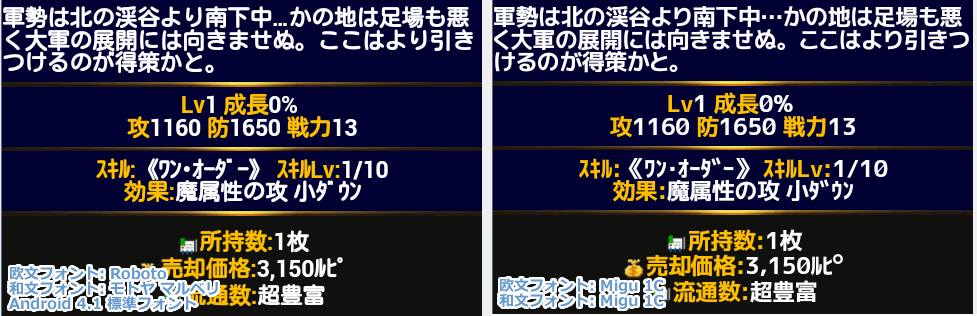
このゲームはなぜかbold体(太字)を使っているが、regularでも三点リーダーの見え方は同じだ。
Android 4.1 標準フォント環境では、三点リーダーは文字の下端に位置する。
欧文フォントもMigu 1Cにすると、三点リーダーは文字の中央の高さになる。
欧文フォント Roboto は「文字の下端に位置する三点リーダー」のglyphを持っていて、Migu 1Cは「文字の中央の高さに位置する三点リーダー」を持っているので、こういうことになる。
Android 4.1 標準フォントの「三点リーダーは文字の下端」は、なんとなく気になることもあるが、スマートフォンユーザーのみなさんは特に違和感を感じていないようだ。
わたしは実際の環境では、欧文フォントを変更すると文字幅の関係で文字が欠けたりするそうなので、和文フォントだけMigu 1Cに置き換えている。
だから毎日、「文字の下端にくる三点リーダー」を見ているのだか、これでも別にいい気がしている。